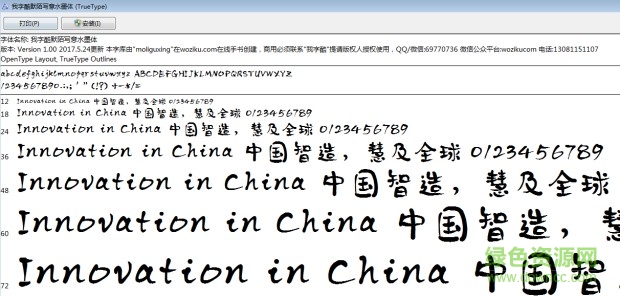
軟件介紹 軟件標(biāo)簽: 我字酷 字體 我字酷默陌寫意水墨體擁有非常濃郁的古風(fēng)色彩,每一筆每一劃都充滿了古韻,中華字體本就博大精深,這款字體更加能體現(xiàn)字形之美,有喜歡的朋友趕緊來綠色資源網(wǎng)下載吧!我字酷默陌寫意水墨體預(yù)覽安裝方式1、首先選中你下載的打包字體,并解壓你下載的字體壓縮包;2、Win Vista\Win 7\Win 8系統(tǒng):鼠標(biāo)右鍵單擊字體文件,然后點擊 > "Install" 安裝字體;3、Windows XP(2000\98)系統(tǒng):把解壓好的字體文件放入 C:\Windows\Fonts 目錄中即可。 軟件截圖 上一張下一張(1 / 1) 安裝詳細(xì)截圖 猜你喜歡 默陌字體 默陌字體 默陌字體是一系列小眾字體,以手寫字體風(fēng)格為主,種類較豐富、具有不錯的藝術(shù)效果,適合廣告設(shè)計、海報設(shè)計、藝術(shù)創(chuàng)作等等各個方面,歡迎大家來綠色資源網(wǎng)踴躍下載使用! 查看更多>> 默陌靜墨飄逸體字體 3.22M/中文/2.0/下載 默陌肥圓水墨體字體 3.40M/中文/3.3/下載 小豆島默陌肥圓手寫簡 2.36M/中文/5.0/下載 小豆島默陌樂童簡 2.29M/中文/6.0/下載 小豆島默陌枝椏簡 3.09M/中文/5.0/下載 默陌歪歪圣誕體字體 2.40M/中文/5.0/下載 其他版本下載 標(biāo)題 大小 更新日期 下載 我字酷無非 1.32M 2017-02-25 下載 靜之字體 12.11M 2017-06-14 下載 我字酷默陌枝椏字體 2.45M 2017-08-17 下載 下載地址 電腦版 我字酷默陌寫意水墨體字體 免費版 點擊報錯 軟件無法下載或下載后無法使用,請點擊報錯,謝謝! 關(guān)閉報錯反饋 請描述您所遇到的錯誤,我們將盡快予以修正,謝謝! *必填項,請輸入內(nèi)容 本類最新 dreamweaver字體庫 首爾南山體字體 v1.06 官方版 潮字社風(fēng)云簡ttf 潮字社凌渡鯤鵬簡體字體 潮字社曾玉波手書簡字體 微博慧心字體 相關(guān)文章 Photoshop字體安裝使用方法和技巧 如何解決“無法新增字體”問題 Win 7系統(tǒng)安裝字體方法 網(wǎng)頁字體大小設(shè)置方法 怎么改網(wǎng)頁字體大小 在Linux系統(tǒng)中安裝字體的幾種方法 windows7字體顯示問題:打開某些程序的時候顯示的是亂碼 用戶評論 熱門評論 最新評論 發(fā)表評論 查看所有評論(0) 昵稱: 請不要評論無意義或臟話,我們所有評論會有人工審核. 字?jǐn)?shù): 0/500 (您的評論需要經(jīng)過審核才能顯示)